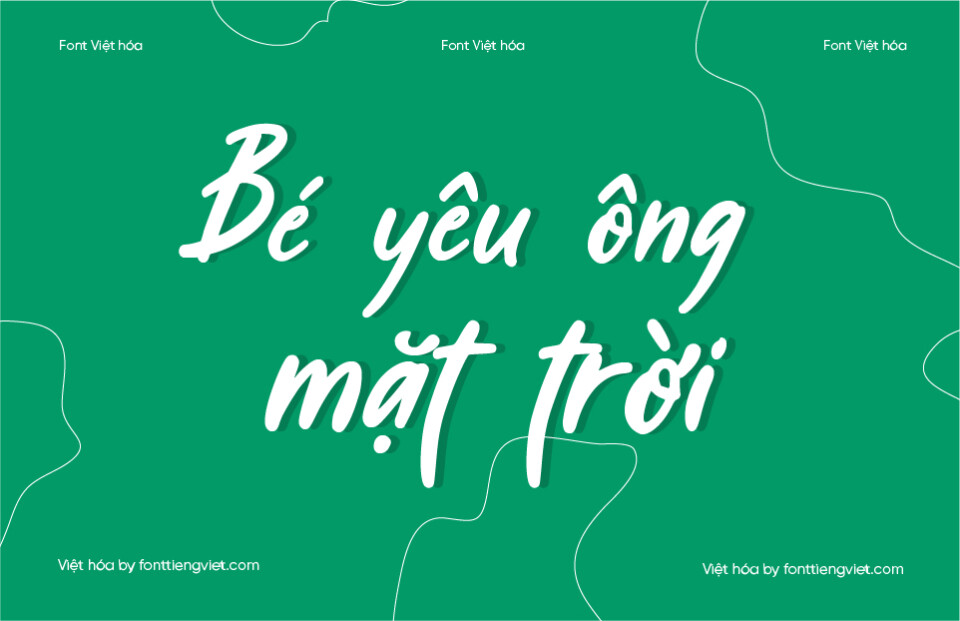
Trong thế giới thiết kế đồ họa và tài liệu học thuật, việc lựa chọn một Font Chữ không chỉ đơn thuần là vấn đề về thẩm mỹ, mà còn là yếu tố quyết định đến sự chuyên nghiệp và khả năng truyền tải thông điệp. Ngày nay, cộng đồng thiết kế Việt Nam đang sôi sục với một cái tên mới: Font Việt hóa 1FTV VIP SS Delight. Đây không chỉ là một bộ font đẹp mắt mà còn là sự kết hợp hoàn hảo giữa phong cách hiện đại và sự tối ưu hóa cho tiếng Việt. Sự Việt hóa tỉ mỉ giúp bộ font này trở nên linh hoạt, dễ đọc, và đặc biệt quan trọng cho các dự án học đường, từ bài thuyết trình đến luận văn tốt nghiệp. Hãy cùng khám phá tại sao bộ font này lại trở thành lựa chọn hàng đầu cho các nhà thiết kế và học sinh, sinh viên.
Giới Thiệu Chi Tiết Về Font Việt hóa 1FTV VIP SS Delight
Bộ font 1FTV VIP SS Delight ban đầu đã nổi tiếng với phong cách thiết kế độc đáo, mang hơi hướng hiện đại nhưng vẫn giữ được nét thanh lịch cần thiết. Tuy nhiên, đối với người dùng Việt Nam, vấn đề lớn nhất luôn là khả năng hỗ trợ các dấu thanh (á, à, ã, ạ, ả…). Quá trình Việt hóa chuyên sâu đã giải quyết triệt để vấn đề này, đảm bảo rằng mọi ký tự tiếng Việt đều được hiển thị một cách trọn vẹn và chuẩn xác nhất. Việc này cực kỳ quan trọng đối với học sinh trung học phổ thông khi chuẩn bị các tài liệu quan trọng cho kỳ thi tốt nghiệp hoặc các báo cáo khoa học. Chất lượng hiển thị đồng nhất của bộ font này giúp tăng cường tính chuyên nghiệp cho bất kỳ văn bản nào. Các chuyên gia SEO cũng đánh giá cao việc sử dụng font chữ rõ ràng, dễ đọc, góp phần cải thiện trải nghiệm người dùng trên các nền tảng trực tuyến.
Đặc Điểm Nổi Bật Của Phiên Bản VIP SS Delight
Điều làm nên sự khác biệt của phiên bản VIP SS Delight chính là sự tinh chỉnh về độ dày nét và khoảng cách giữa các ký tự (kerning). Các nhà phát triển đã tối ưu hóa font để nó hoạt động tốt trên cả môi trường in ấn và kỹ thuật số, đặc biệt là trên màn hình độ phân giải cao. Sự cân bằng hoàn hảo này mang lại một trải nghiệm thị giác “Delight” đúng như tên gọi. Đối với các dự án cần sự sáng tạo nhưng vẫn giữ được sự nghiêm túc, như thiết kế bìa sách hoặc poster cho các sự kiện của trường, bộ font này cung cấp một giải pháp lý tưởng. Nó dễ dàng thu hút sự chú ý mà không gây cảm giác rối mắt hay quá cầu kỳ.
Tại Sao Font Chữ Này Lại Được Ưa Chuộng Trong Cộng Đồng Học Thuật và Thiết Kế?
Sự ưa chuộng của bộ font này không chỉ đến từ vẻ ngoài mà còn từ tính ứng dụng rộng rãi. Trong môi trường học thuật, tính rõ ràng và dễ đọc luôn được đặt lên hàng đầu. Một luận văn hay báo cáo có nội dung xuất sắc nhưng trình bày kém có thể bị giảm điểm đáng kể. 1FTV VIP SS Delight giúp các tài liệu của học sinh, sinh viên trở nên chỉn chu và dễ theo dõi hơn.
Ưu Điểm Về Tính Thẩm Mỹ và Chuyên Nghiệp
Tính thẩm mỹ của Font Việt hóa 1FTV VIP SS Delight thể hiện qua các đường nét mềm mại, hiện đại. Nó thoát khỏi sự cứng nhắc của các font truyền thống như Times New Roman hay Arial, nhưng vẫn giữ được sự chuyên nghiệp cần thiết. Đây là yếu tố quan trọng khi các bạn trẻ muốn tạo dấu ấn cá nhân trong các dự án sáng tạo. Các nhà thiết kế đồ họa sử dụng font này cho các tiêu đề lớn, logo, hoặc các ấn phẩm đòi hỏi sự đột phá về mặt thị giác. Độ tương phản cao và các glyphs được thiết kế cẩn thận giúp font này duy trì chất lượng hiển thị ngay cả ở kích thước nhỏ.
Ứng Dụng Thực Tế Cho Sinh Viên và Học Sinh
- Báo Cáo và Tiểu Luận: Tạo điểm nhấn cho tiêu đề chương và phụ lục, làm tăng tính hấp dẫn của bài viết.
- Slide Thuyết Trình: Đảm bảo sự rõ ràng khi chiếu trên màn hình lớn, giúp người nghe tập trung vào nội dung.
- Dự Án Tốt Nghiệp: Mang lại cái nhìn hiện đại, thoát khỏi sự nhàm chán của các tài liệu học thuật truyền thống mà vẫn giữ được tính nghiêm túc, đặc biệt quan trọng trong các kỳ thi tốt nghiệp trung học phổ thông.
- Thiết Kế Poster/Infographic: Dễ dàng kết hợp với các yếu tố đồ họa khác nhờ vào sự linh hoạt trong phong cách.
Tóm lại, Font Việt hóa 1FTV VIP SS Delight không chỉ là một tài nguyên thiết kế, mà là một công cụ mạnh mẽ hỗ trợ đắc lực cho mọi đối tượng, đặc biệt là học sinh, sinh viên trong quá trình chuẩn bị cho các dự án quan trọng và kỳ thi tốt nghiệp. Với sự tối ưu hóa hoàn hảo cho ngôn ngữ Việt Nam, nó đảm bảo tính thẩm mỹ, độ chuyên nghiệp và khả năng đọc tuyệt vời. Đừng ngần ngại bổ sung bộ Font Chữ đặc biệt này vào bộ sưu tập của bạn để nâng tầm chất lượng các sản phẩm sáng tạo. Việc đầu tư vào typography chất lượng chính là đầu tư vào sự thành công của thông điệp mà bạn muốn truyền tải.